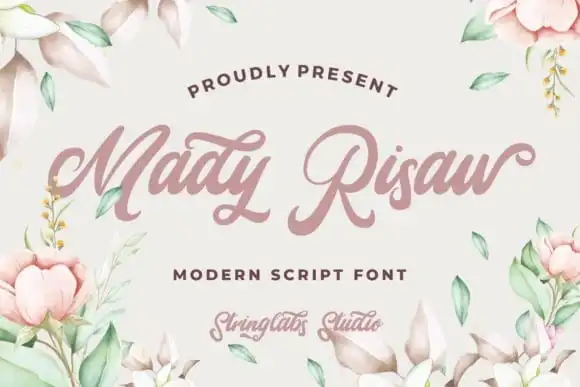
A Mady Risaw Script Font é uma elegante fonte para letras cursivas feita à mão que chama atenção por sua riqueza em detalhes e fluidez. Inspirada nos designs clássicos de tipografia dos anos 60 até os 80, essa fonte se destaca não apenas pela sua delicadeza e elegância, mas também pela sua proporção perfeita entre as letras. Este tipo de fonte é perfeito para quem busca uma paleta vibrante para projetos criativos, seja em logotipos ou editoriais de texto. Sua facilidade na adaptação a diferentes estilos torna-a uma excelente escolha para aqueles que buscam uma fonte versátil capaz de dar vida e personalidade a seus conceitos mais imaginativos. Para quem busca um toque especial em suas criações, a Mady Risaw Script Font é uma ótima adição à sua biblioteca de fontes.